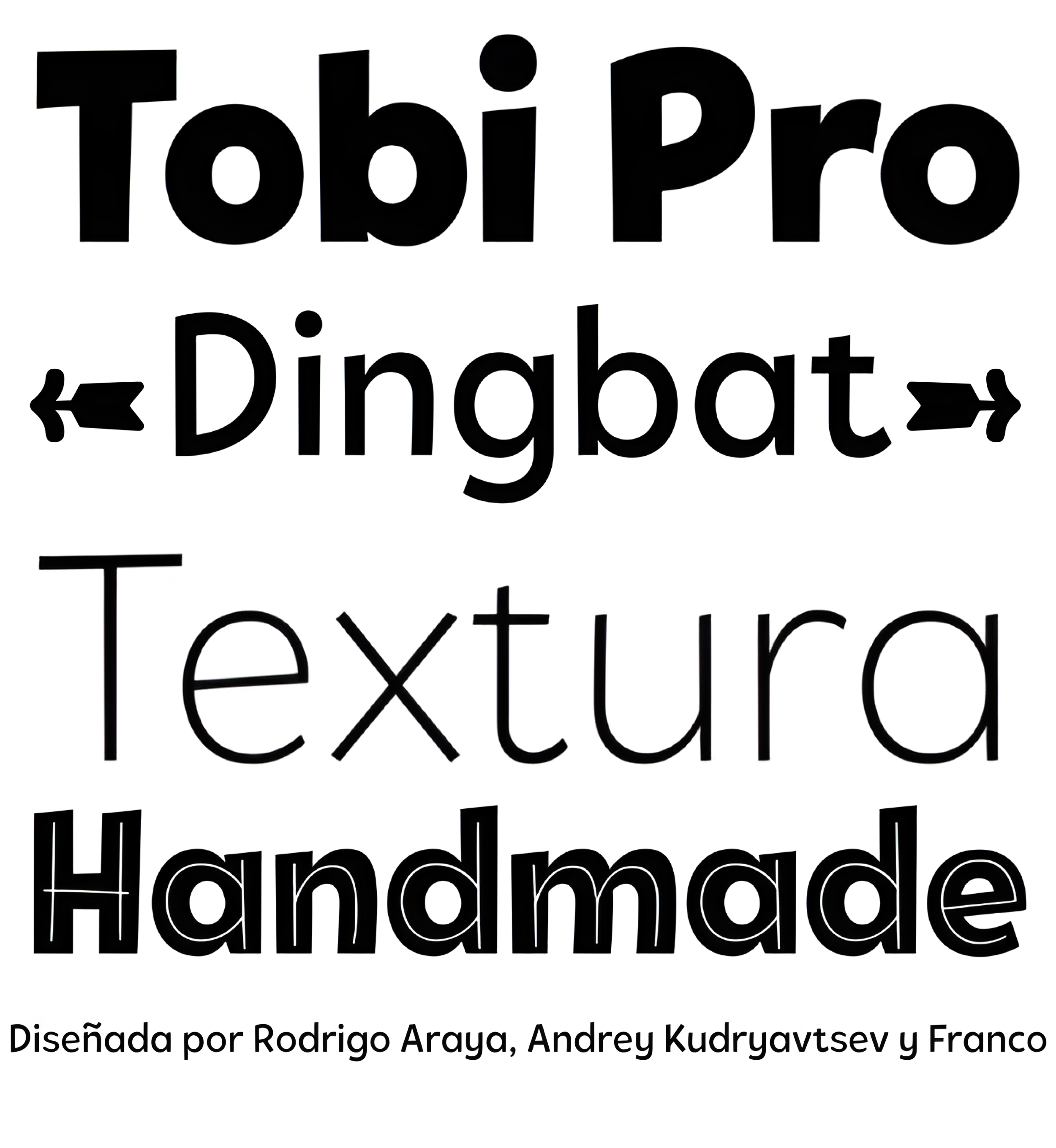
| Créditos | Andrey Kudryavtsev, Rodrigo Araya Salas, Franco Jonas |
| Descripción | La familia tipográfica Tobi Pro fue diseñada por Andrey Kudryavtsev, Rodrigo Araya Salas, Franco Jonas y publicada por RodrigoTypo. Tobi Pro contiene 13 estilos y opciones de paquete familiar. Tobi Pro - la nueva versión de Tobi "el año anterior" - es una familia tipográfica geométrica con un toque orgánico. Contiene 7 divertidas variantes, sombras, dingbats y efectos para la variante Heavy, además cuenta con alternativas OpenType en todas sus variantes. Tobi es una tipografía perfecta para carteles, envases, logotipos y cualquier aplicación de comunicación visual inherente a diseños infantiles y juveniles. |
| Familia(s) | Tobi Pro Dingbat, Tobi Pro Heavy, Tobi Pro Extra Bold, Tobi Pro Dingbat Rough, Tobi Pro Heavy Bonus Line, Tobi Pro Dingbat Hand, Tobi Pro Heavy Bonus Shadow, Tobi Pro Light, Tobi Pro Heavy Bonus One, Tobi Pro Medium, Tobi Pro Regular, Tobi Pro Ultra Light, Tobi Pro Thin. |
| Fundidora | RodrigoTypo |
| Reconocimientos | Bienal de Tipografía Latinoamericana. Tipos Latinos 2022 |